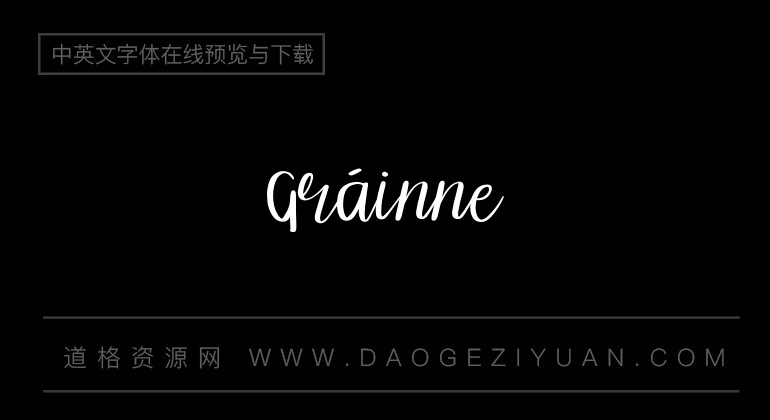
Gráinne字体是一款现代感十足的新字体,它拥有更高的粗体和锐利的轮廓,以及更大的字母间距,让您的设计充满活力。它的字体设计具有独特的风格,可以满足您的各种设计需求。它的字母形状和轮廓清晰可见,可以提供更多的灵活性,可以让您的设计更加精美。它的细节设计也很出色,可以使您的设计更加精致。内容介绍
Gráinne是一款非常不错的手写艺术字体,具有很好的视觉感,适合于文化类的宣传设计、商业类品牌的广告和产品包装设计以及个性化文字排版等较多场景。